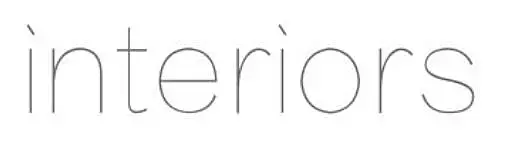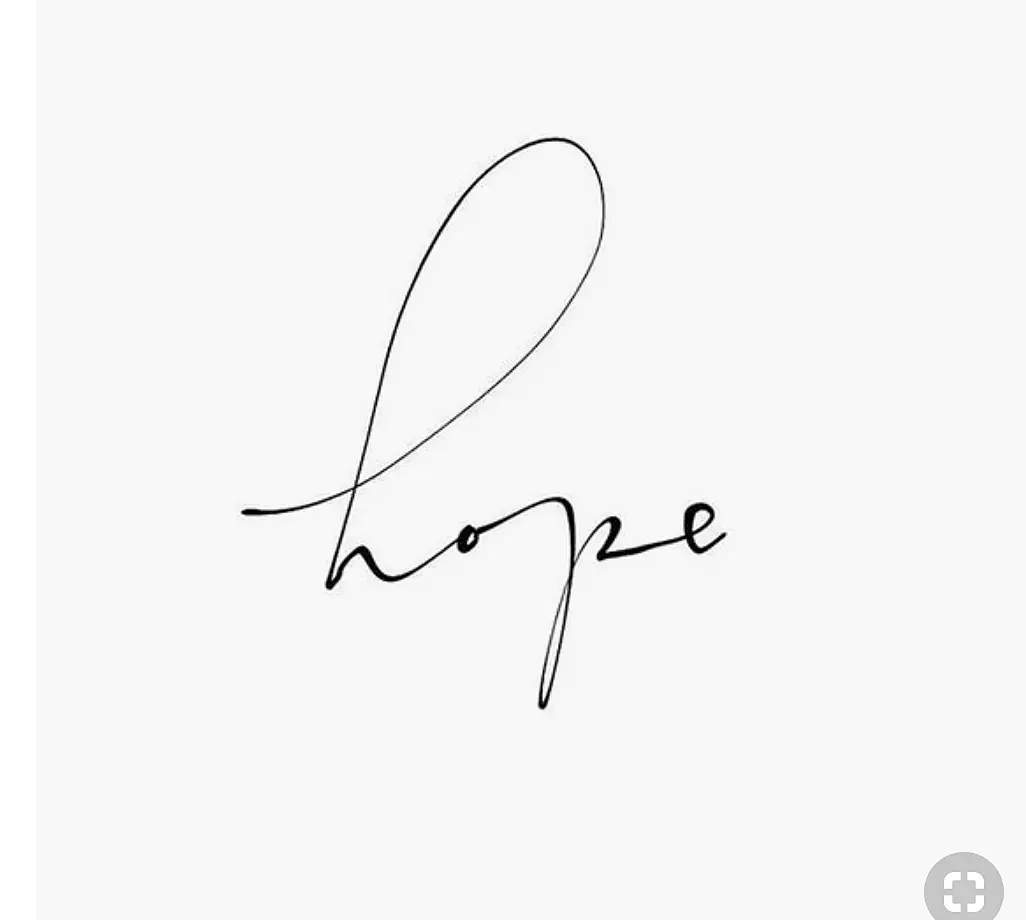
Помогите распознать шрифт
Помогите найти такой шрифт .... спасибо !!
Дожил. Не могу найти простой , почти системный шрифт)
Цитата outgribe:
типа да, только у "i" точка со скосом.
Добрый день. Подскажите, как называется такой шрифт? Может кто встречал. Не могу подобрать
похожие #1, #2